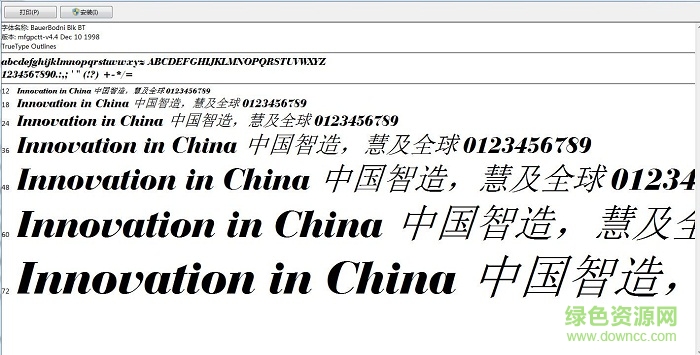
bauerbodni blk bt-普通常規(guī)體
bauerbodni blk bt-常規(guī)斜體和普通常規(guī)體是小編為大家整理的兩款英文襯線字體包,線條優(yōu)美,布白得當(dāng),排版效果良好,十分實(shí)用,歡迎需要的朋友前來(lái)下載!
襯線與無(wú)襯線字體介紹
【無(wú)襯線字體】
現(xiàn)代Sanserif的起源并不算很久,也就100多年的歷史。沒(méi)有裝飾的成份,具有較好的可讀性成為它的最大武器。起初由于它那打破傳統(tǒng)的前衛(wèi)造型,而被保守人士所排斥,在德國(guó)它更因此被稱做Grotesque(意即丑陋的)。當(dāng)它被傳入美國(guó)時(shí)被誤解為歌德體,至今仍被稱做Gothic。隨著現(xiàn)代設(shè)計(jì)的發(fā)展,Sanserif字體已被廣泛的為大家所熟識(shí)和使用。
bauerbodni blk bt-普通
【襯線字體】
擁有Serif的字體,一般都可以稱做Serif字體。Serif中文有翻譯作“襯線”或“線腳” 的,起源類似于中國(guó)宋體字中橫筆的三角造型。古代羅馬文字的書(shū)寫(xiě)是用扁平的筆,而我 們現(xiàn)在看到的Serif也是在實(shí)際書(shū)寫(xiě)過(guò)程中自然形成的。Serif的造型各異,可以說(shuō)是判斷 Serif字體中各個(gè)細(xì)分類別的最重要參考造型之一。